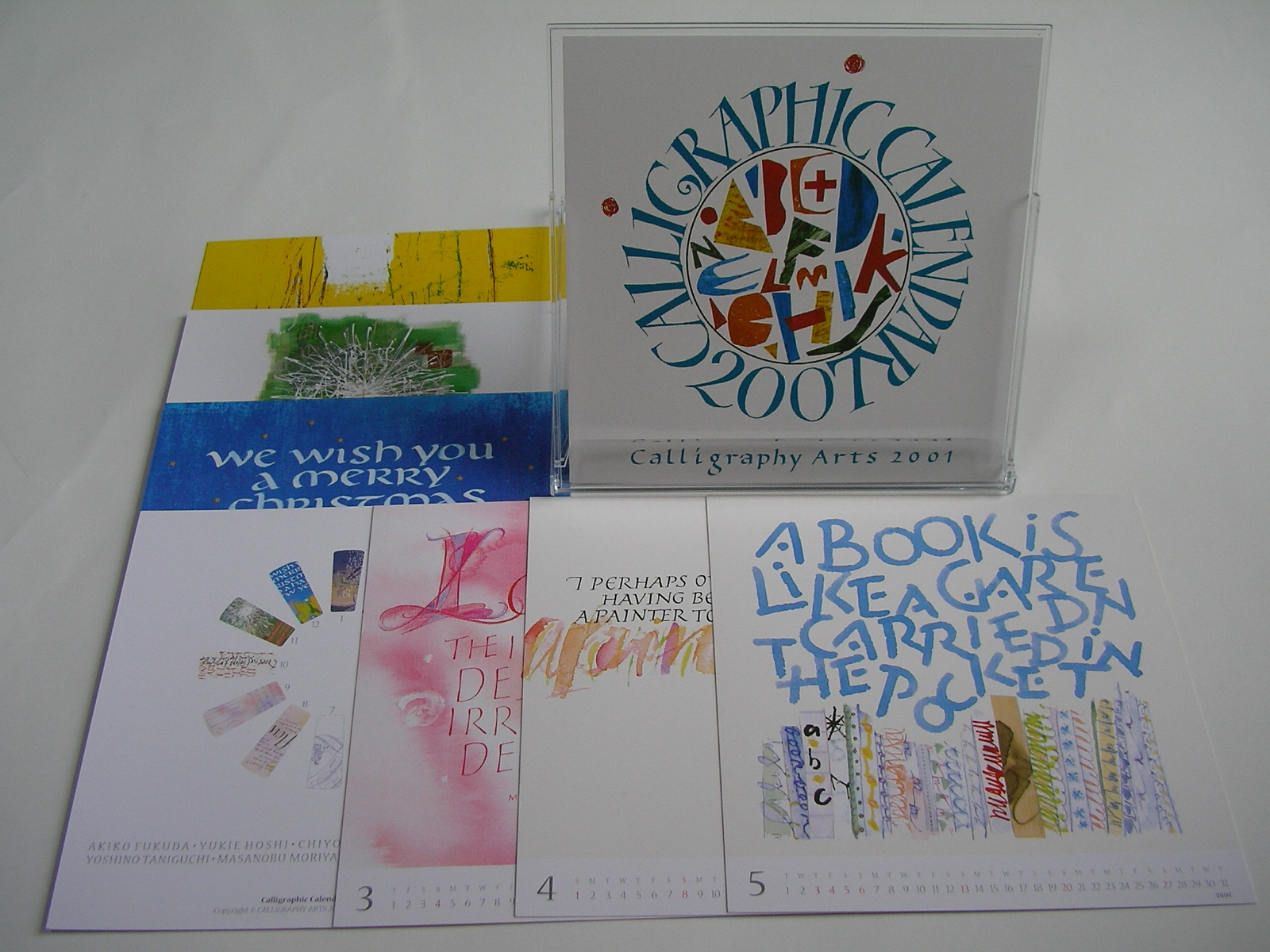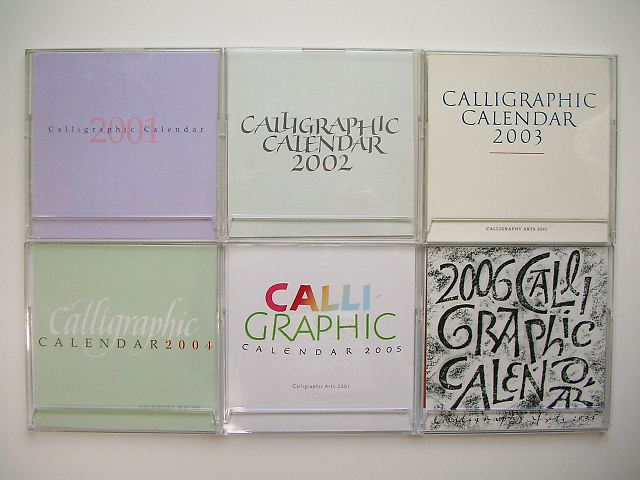
ですので、デスク用はA5サイズのノート式で、スケジュールは1日を縦に区切った形にしています。
今気になっているのはこちらの手帳。佐々木かおりさんのイーウーマンの手帳です。
アクションプランナー
このサイトではこんな風に説明しています。
「アクションプランナーとは行動計画帳、という意味です。手帳を、時間という点でとらえて約束ごとを書くだけの使い方から、自分の人生の脚本を書くための行動計画帳、というイメージにふくらませる。時間を面でとらえ、時間帯に何をするのか、という行動を書いていくための手帳です。」
ほほ〜、人生の脚本だそうです!このごろでは、手帳と共に使い方の本も出ているんですね。夢を実現するには、手帳を活用して行動計画をせねばならんっちゅうことですね!
ほぼ日からも出ています。ほぼ日手帳の秘密―10万人が使って、10万人がつくる手帳。
1年間の予定を立てるのはとても楽しく夢が膨らみますが、使い方を変えるだけで、夢が叶うなら試しにやってみてもいいかもね。
3日坊主にならない様に、やるなら誰かに宣言するといいかもよ〜!
Tom Schulten
もう今年になって半年も過ぎてのご紹介ですが、教室にかけてあるカレンダーはTom Schultenのものです。
この作家がどういう人かは全然知らずに購入しました。色がきれいで分割して塗られている手法がとても面白いと思ったからです。
それともお天気の日と曇り空の日が一緒になっているのかも。
この色が暗くなるとこんな色になるのだなぁ、とよくわかります。
Tom Schultenは1938年生まれのオランダの画家で、もとは広告の仕事をしていたそうです。この幾何学的な線で区切られている所がおもしろいし、抽象的で空想的な形を作るための色の対比がとてもすばらしい!
ふ〜ん、ワンコが好きなのかしら〜?手になぜかパレットを持っている姿がおかしいですね!ポーズをと取らされたって感じです。
さて、あと残りの6ヶ月分、これからも毎月このTom Schultenのカレンダーを楽しんで参ります! きれいだからまた来年も購入するかも〜?
カリグラフィー練習カレンダー
クラスのmasayoさんがカリグラフィーを練習出来るカレンダーを、わざわざ持って来て見せてくれました。
前にこれについてお話してくれた時には、なんとなくもっと簡単なものをイメージしていましたが、こんなに立派なものだとは!驚きました。
ご覧の通り、一日一枚のカレンダー。日めくりの様に、書体を練習する事ができるのです。まず最初に書体のa~zが紹介され、次の日から、単語で練習となります。
そして毎日練習!
masayoさんはちゃんと1月の分は練習してありましたよ、素晴らしい!
アマゾンで購入出来るそうですが、その時に「この本を買った方はこんな本も・・・・」という本が紹介されていますよね、それにmasayoさんやられちゃったそうです。
で、一緒に購入したのがこれ。
この5色で色を作るのかしら〜。難しそうだけど、気軽に楽しもうと思えば結構面白いかもしれませんね。
昔、Marsha Bradyというカルフォルニア在住のカリグラファーに習ったことがありますが、彼女は「上手になりたかったら、とにかく毎日少しで良いからペンを持って書く様に。一日に一回は机に向かうこと」とアドバイスしていました。
こういう楽しいものがあれば、一日一枚、自然と練習できるかな〜?
バースデーカレンダーみっけ
見つけました!バースデーカレンダーです。
先週神戸へ行った時に少しだけ時間があったので北野へ行きました。こじゃれたお店がい〜〜っぱい。輸入ものを扱っている雑貨屋さんで発見!ダッシュでゲット。
文字がいいでしょう!書いたと言うより切りぬいて貼ったみたい。
中はいたってシンプル。日にちの所に名前が書ける様になっているだけです。実用的。
私が最も気に入ったのは、月の数字のデザインがおもしろいところです。横向きだったり、たくさんだったり、はみ出たり。
よく見るとすべて同じ形ではないから、ひとつひとつ書いたのか切り取ったのか。
色が白と赤だけというところがいいね。私の生まれ月の3月が可愛いのますます嬉しい。
もうすぐ一年が終わりますが、来年こそ、このカレンダーに名前をたくさん書いてバースデーカードを差し上げたいものでーす。
2007カリグラフィックカレンダー
来年のカレンダーが、街のショップににぎやかに並ぶ季節になりました。
そして、今年もモジトルのメンバーも参加しているCalligraphy Arts 2001の2007年カリグラフィックカレンダーも無事出来上がりました。
今回7回目、mojitor-sさん担当の表紙は、インパクトがあって注目必至です。そして、中身も負けじとカラフルな印象の12ヶ月一揃いのカレンダーに仕上がりました。
毎回、全体がどんな感じになるか本当に楽しみですが、期待を裏切らない8名の個性の協演は圧巻!
まあ、カレンダーの用途には、多少薄いかもしれませんが(十分機能ははたします!)カリグラフィーの小作品集として満足いくものと思っています!
とはいえ、印刷の悲しさで、オリジナルの色、質感の再現は不可能、オリジナルにまさるものなく、その良さをお見せできないのが残念無念!そろそろまた展示会をして、オリジナルを披露する時期かもしれません。
やけに自信たっぷりのコメントになっています????????
いえいえ、実物をみていただければきっと納得です!
さて、いつも悩むのが印刷数量です。500個にするには、あまりに遠く、400個にするには、ちょっと足りないかもという具合です。そんな中、これまでは、楽観的に余剰数量を加味してつくってみましたが、善処策として、今回予約をとる方向でやってみたところ反応いまいちだったこともあり、気弱に余剰なしの数量にしました。すると、早、完売御礼!!!!!いままでになくレアものとなりました!毎回、楽しみにまっていてくださり、手にして喜んでくださる方にいつも本当に感謝です。
2010年までは継続予定です!どうぞよろしくお願いいたします。